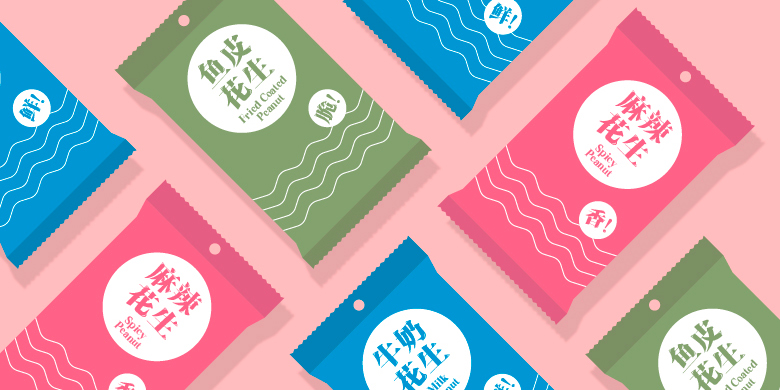
方正手写宋
字体品牌: 方正字库 设计师:刘亢 字体分类:宋体、创意字体、创意书写 字体属性:精品字 字符集:大陆简体(GB2312-80)、简繁扩展(GBK) 发布时间: 2020
手写宋,由宋体字演变而来,笔画活泼个性,俏皮可爱,笔画的倾斜变动、边缘的褶皱设计、以及高光效果的添加,赋予了字体年轻而灵动的态势,同时也让字体更加自然随性,呈现出轻松而欢乐的氛围。
本款字体,适用于产品包装、海报以及banner标题、广告设计等视觉环境,有着较强的适用空间。